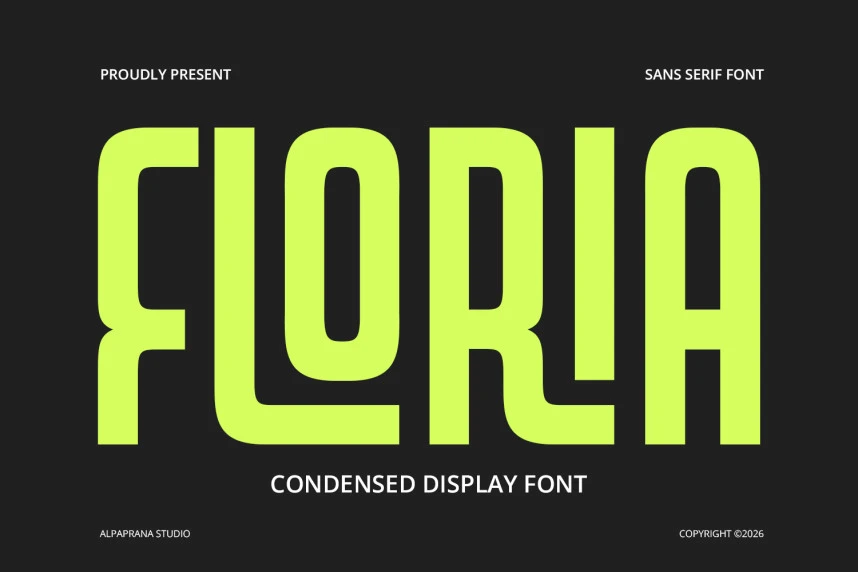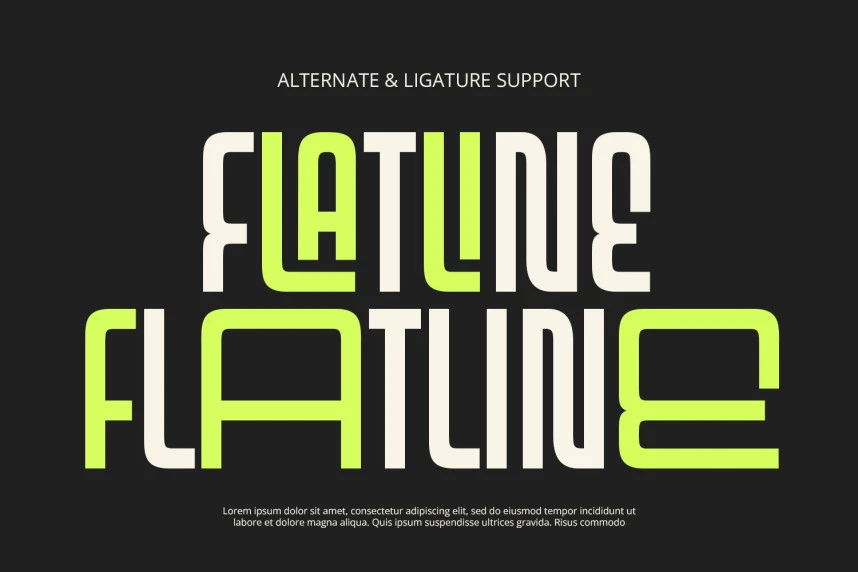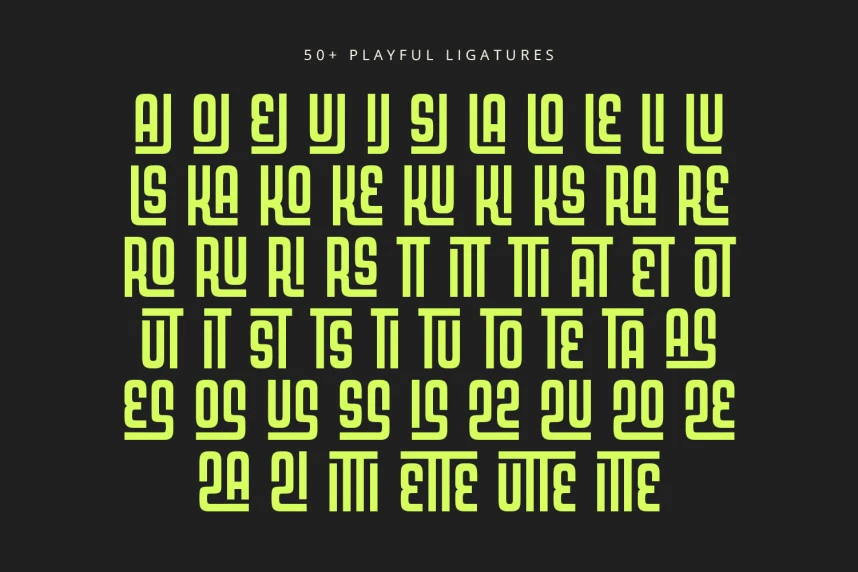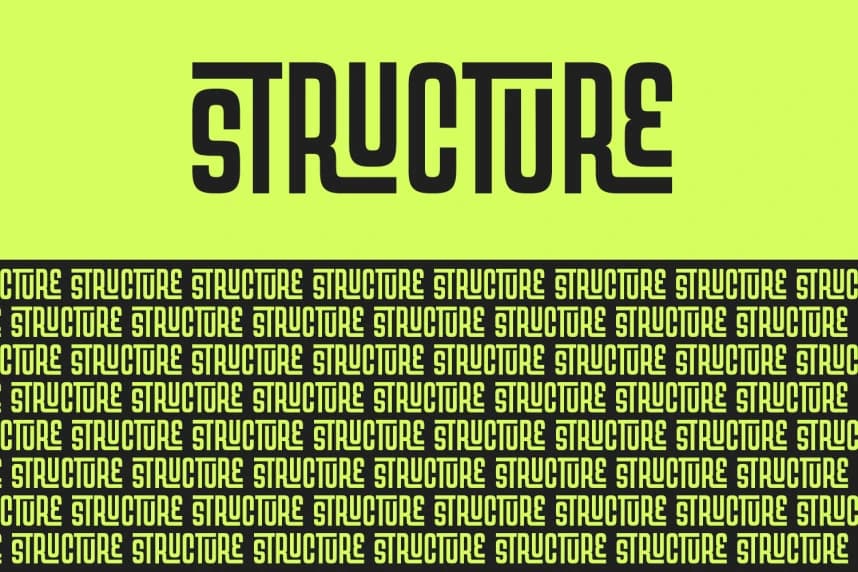
Floria – Display Font
Floria - Display Font, modern bir hissiyat veren bir display yazı tipidir. Branding, Logo Tasarımı, Lettering, Logotype, Giyim, Posterler, Dergiler, Ambalaj, Afişler, Alışveriş Çantaları, Tişörtler, Kapaklar, Fotoğrafçılık, Özel Etkinlikler ve diğer tasarım projeleri için mükemmel bir şekilde kullan
Floria - Display Font, modern bir hissi veren bir gösterim yazı tipidir. Markalaşma, Logo Tasarımı, Harf Tasarımı, Logotip Tasarımı, Giyim, Afiş, Dergi, Ambalaj, Afişler, Alışveriş Çantaları, Tişörtler, Kitap Kapakları, Fotoğrafçılık, Özel Etkinlikler ve diğer tasarım projeleri için mükemmel bir şekilde kullanılabilir.